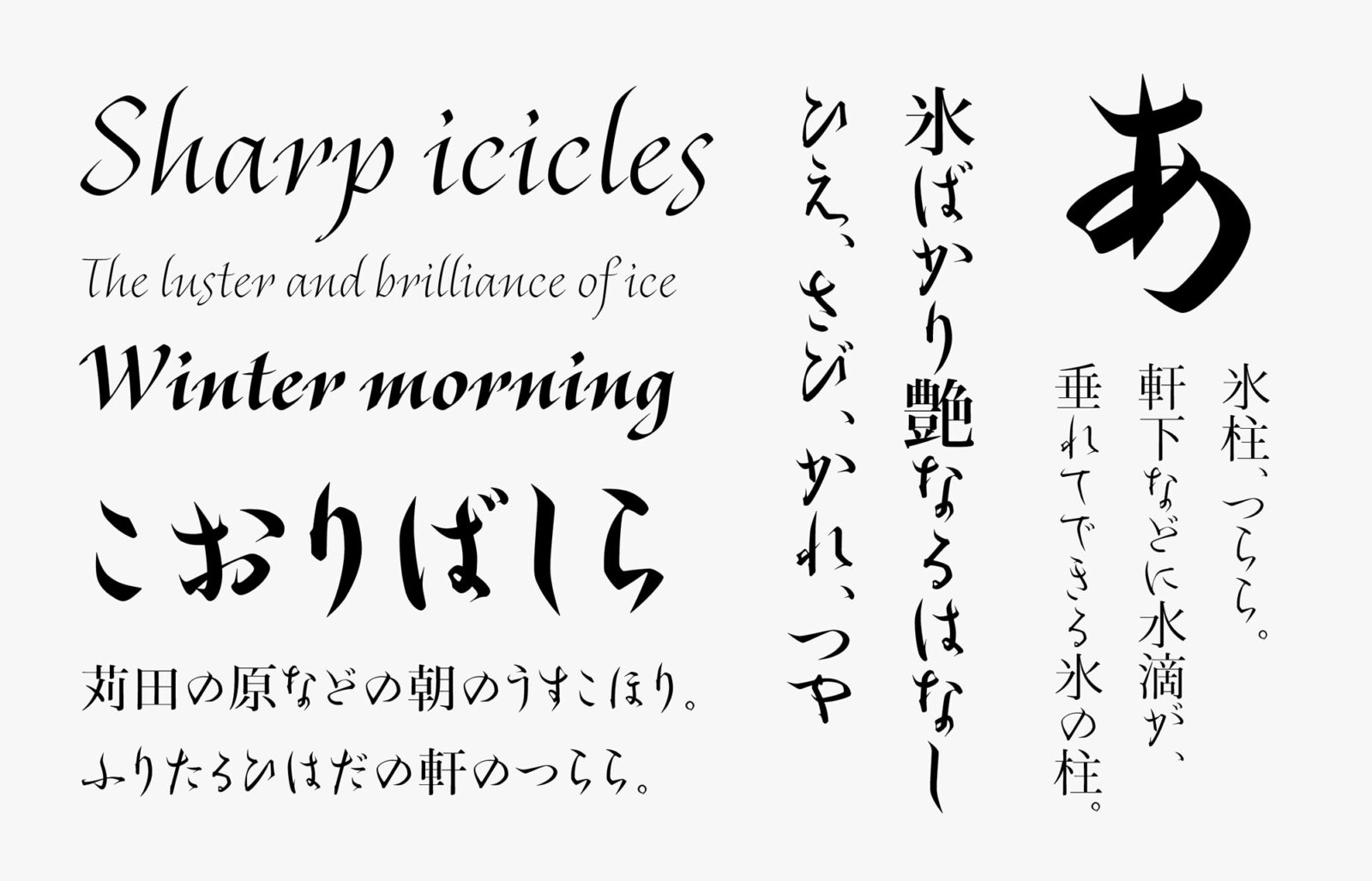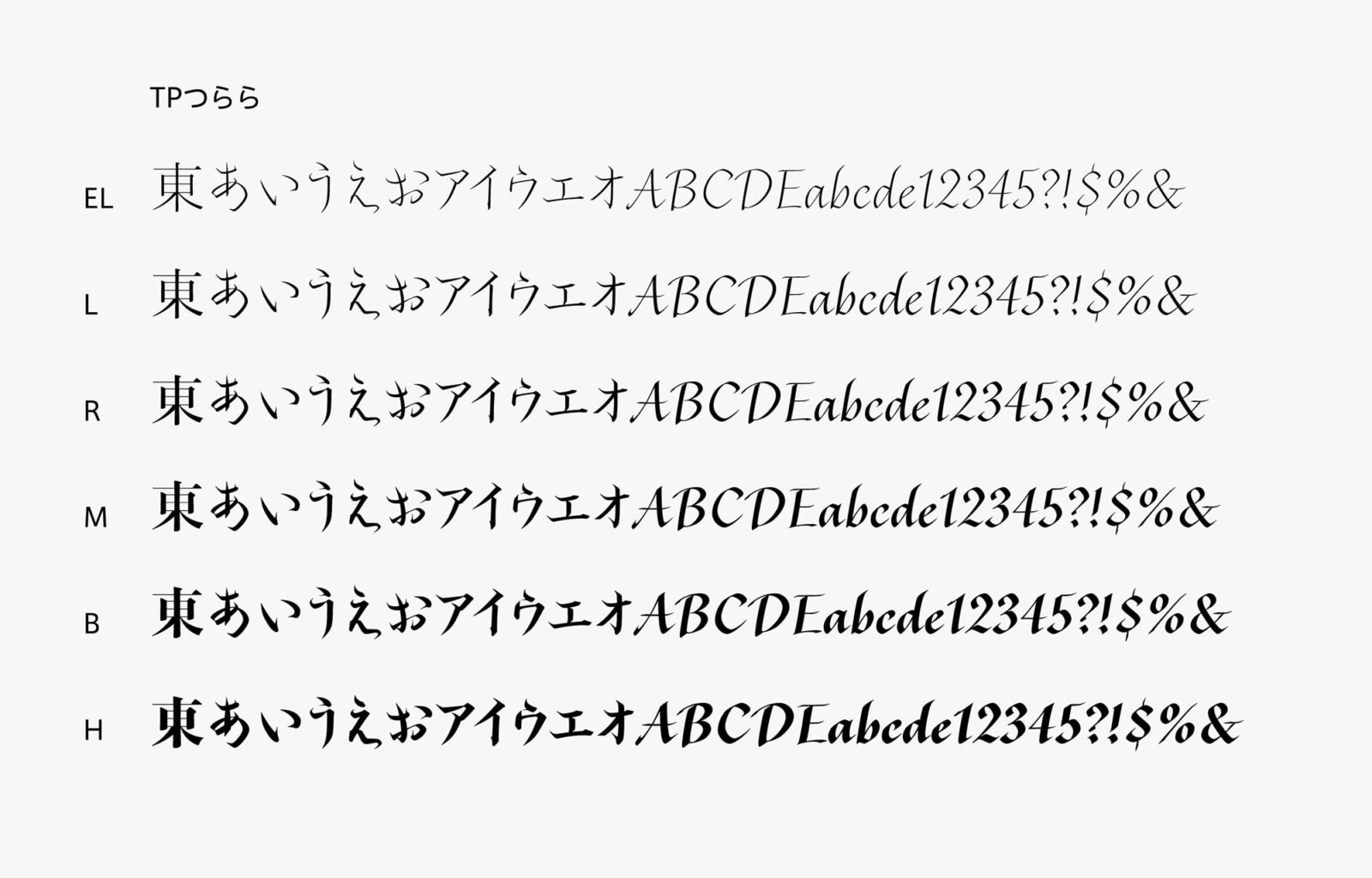
タイププロジェクト、四季フォントプロジェクト第三弾 「TPつらら」の提供を開始
藤原俊成の筆跡を仮名のモデルに、冬の冷たい空気が生み出す氷柱をイメージした書体
タイププロジェクト株式会社(東京都練馬区 代表取締役社長 鈴木 功)は、四季フォントプロジェクトの第三弾として、氷柱をイメージした「TPつらら」を発表しました。本日よりタイププロジェクトのサブスクリプションサービス「TPコネクト」にて提供を開始いたします。
TPつららは藤原俊成の筆跡を仮名のデザインのモデルにした書体で、強い個性をもちながらも現代的な場面でも高い実用性を発揮する書体です。その書体デザインには、冬の冷たい空気が生み出す氷柱をイメージした冷え・寂び・枯れに残る艶のエッセンスを注入しています。欧文は、つららの鋭さを表現するため、ペンによる筆記をベースに書体づくりをおこない、引き締まった空気を感じさせる書体に仕上げました。漢字は、縦画の起筆とウロコの尖り具合が仮名とマッチする濱明朝のヘッドラインを組合せています。
四季フォントシリーズは、四季の風物を書体に反映する「季節性」、詩歌・歌謡をはじめ韻文の表現をゆたかにする「抒情性」、古今東西の良質な文化を受け継ぐ「継承性」を三要素として、日本語をよりゆたかにより繊細に表現することを目指しています。
タイププロジェクトの代表取締役 鈴木 功は、「藤原定家の文字も個性的ですが、実父である俊成の字もほかに類を見ない独特な姿をしています。心敬の『氷ばかり艶なるはなし』という言葉は、俊成に通じる美意識が感じられます。TPつららは、その俊成の文字の魅力を保ったまま現代に通用する書体へと仕上げたと自負しています。四季フォントの見どころのひとつである、漢字と仮名、和文と欧文の響き合いをお楽しみください」と述べています。
TPつららは、鋭い印象のハイコントラストを軸に、EL (Extra Light)からH (Heavy)の6 つのウエイトで構成されています。L (Light)から R (Regular) が、ベースにした俊成の筆跡に近い太さです。